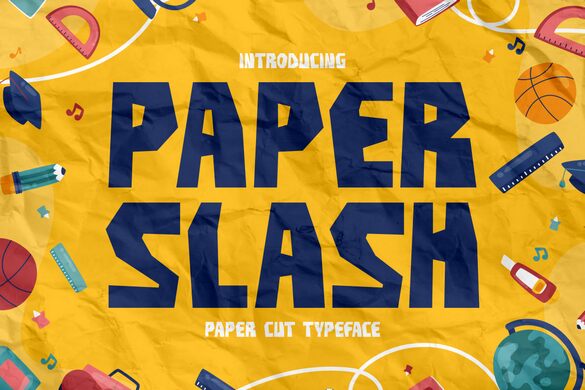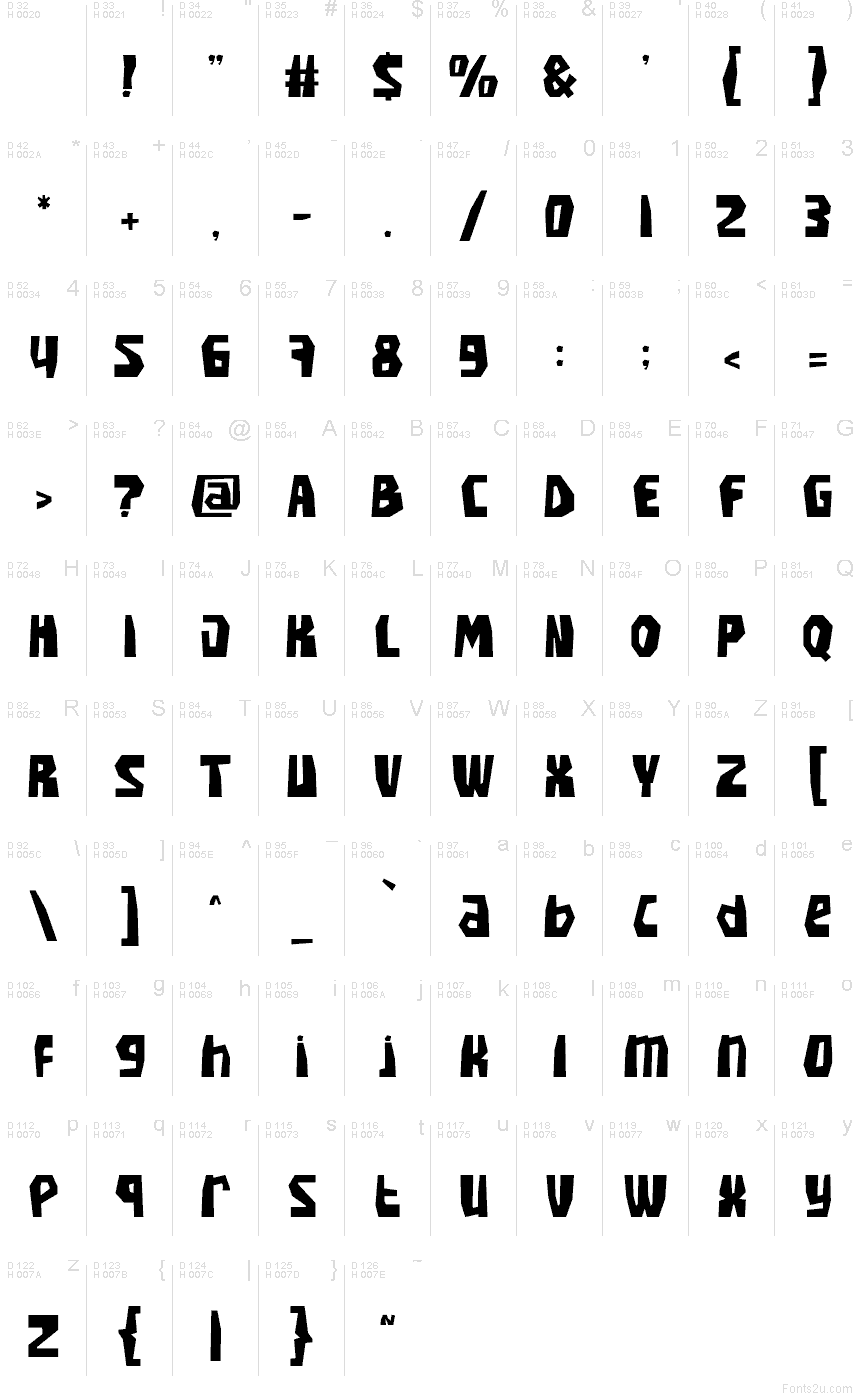
Paper Slash di Shanaf Studio è un font display gratuito in stile carta ritagliata, con lettere che sembrano ricavate da fogli di carta grezza e incollate a mano. Gli angoli irregolari, le silhouette corpose e il ritmo disinvolto le conferiscono un tono artigianale e leggermente dispettoso, che rimanda più a un collage che alla geometria rigorosa.
È l'ideale per poster, grafiche per eventi per bambini, titoli in stile fumetto, copertine di fanzine e packaging giocoso, dove un font gratuito con questa energia strappata e frastagliata può trasmettere subito il messaggio. Usalo soprattutto per titoli brevi e grandi scritte di copertina: le lettere hanno abbastanza brio e carattere da dare vita al testo senza bisogno di illustrazioni aggiuntive.